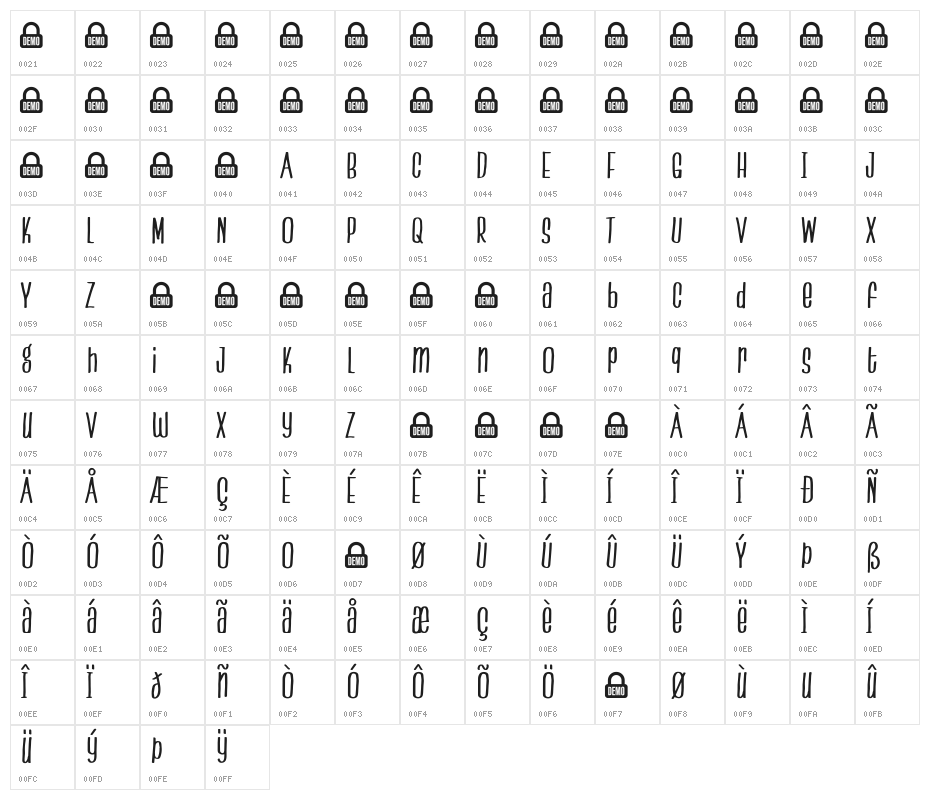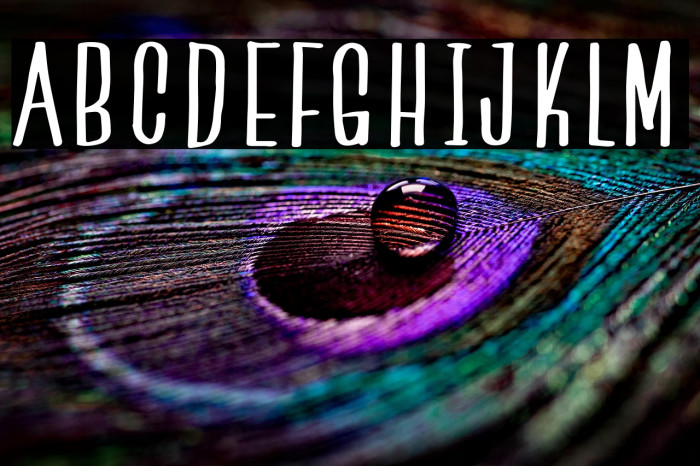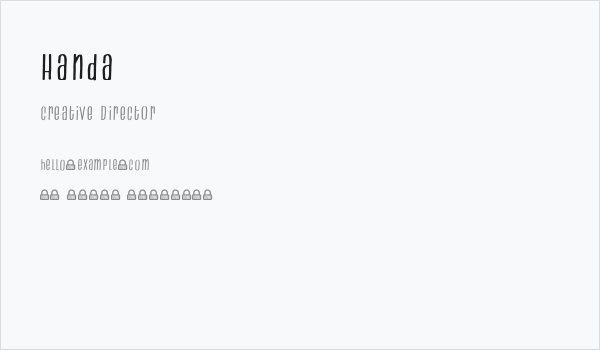
Handa Font
| 分类 | Kids |
| 宽度 | Condensed |
| 整体风格 | Casual, Artistic |
| 使用场景 | Headlines, Posters, Branding |
| 推荐项目 | Ideal for creative projects such as posters, invitations, and branding materials that require a whimsical and artistic touch. |